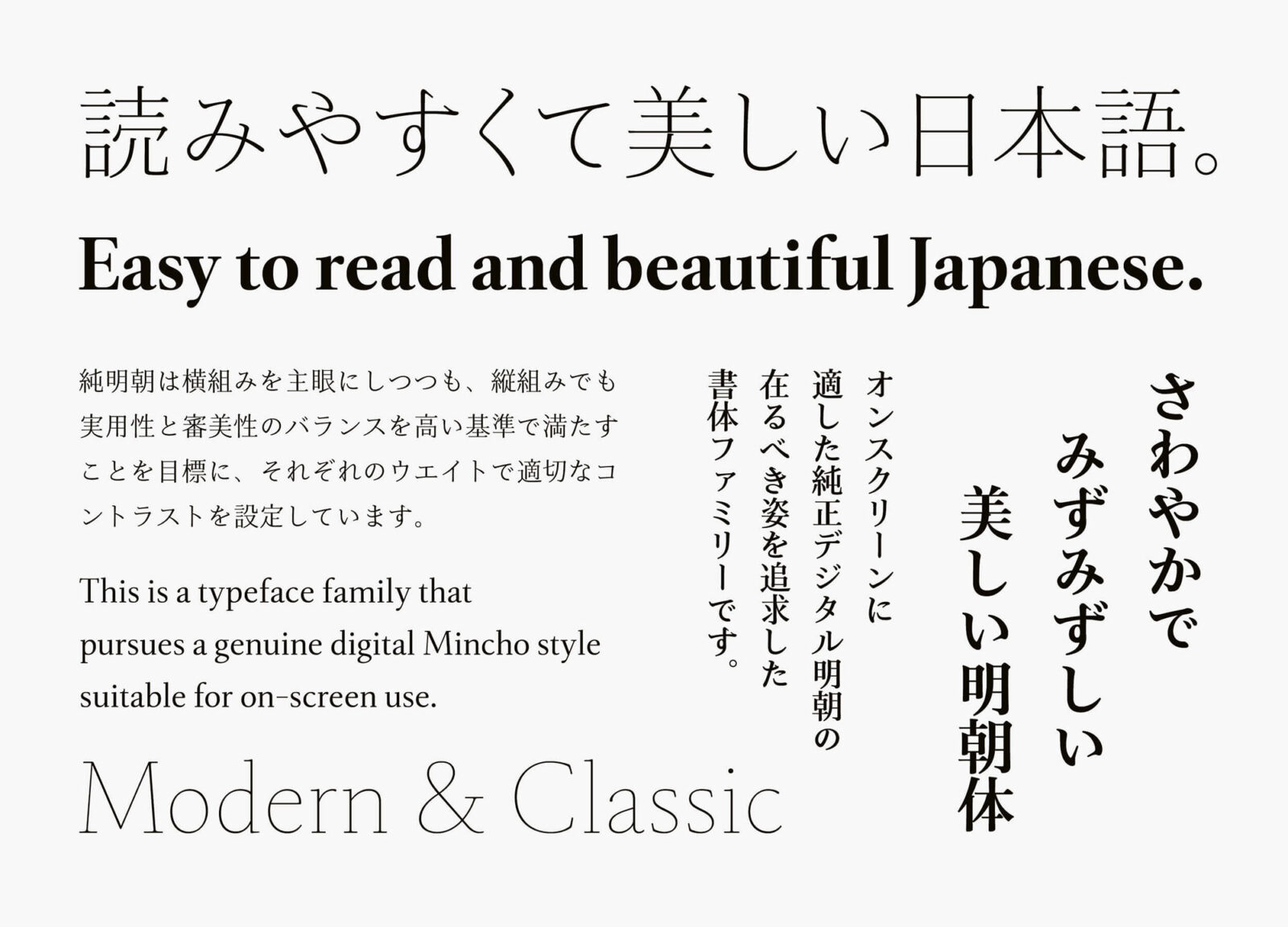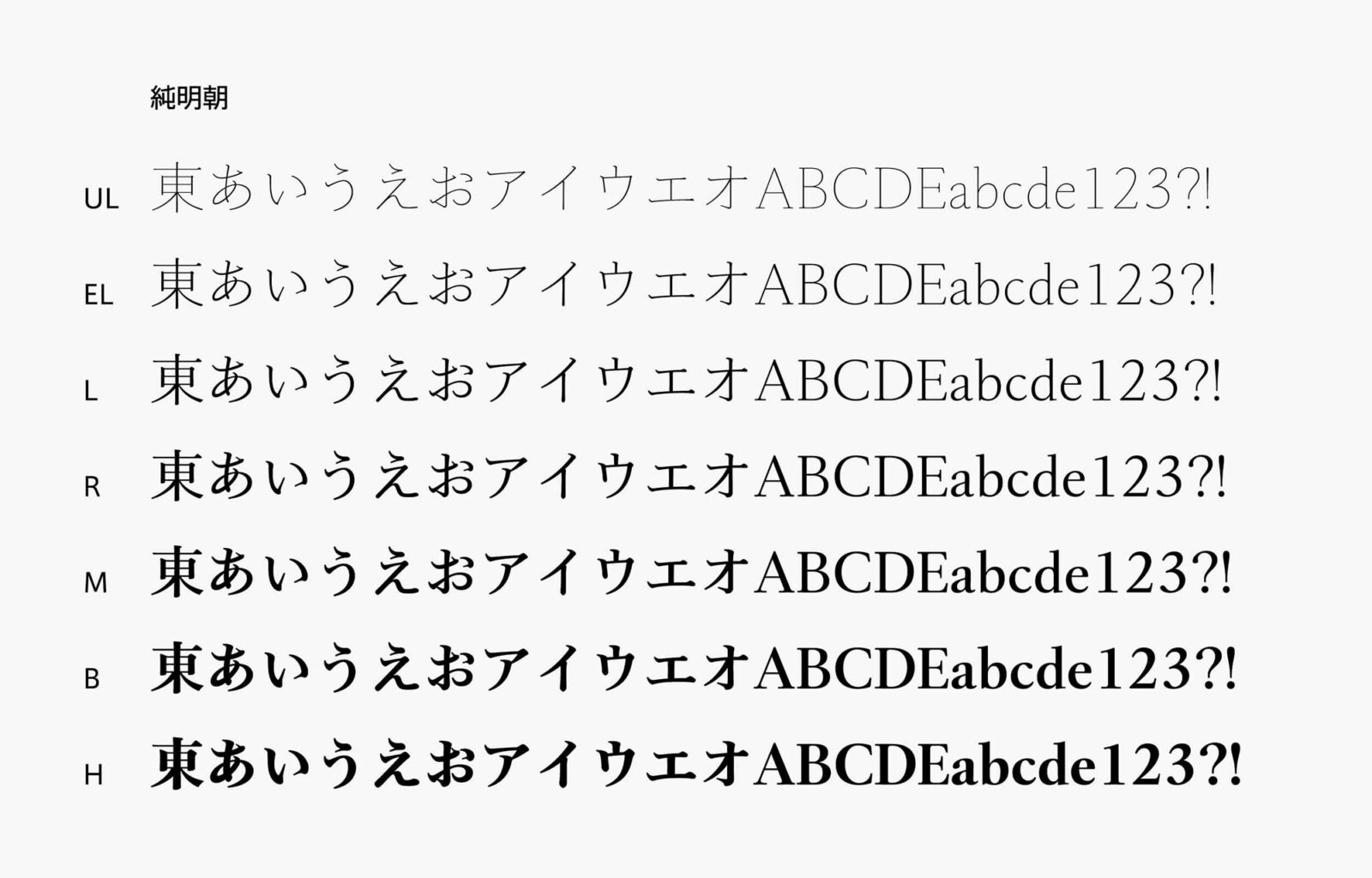
「横組みの日本語をもっと読みやすく、もっと美しく」をテーマにした書体
純明朝は「横組みの日本語をもっと読みやすく、もっと美しく」をテーマにした書体ファミリーで、安定した読み心地が得られるよう、それぞれのウエイトにおいて適切なコントラスト(縦画と横画の太さの比率)を設定しました。オンスクリーンで敬遠されがちな明朝体の弱点を克服するとともに、画面にうるおいを与えるべく明朝体の美しさを十分に引き出す書体設計をおこなっています。
純明朝は、横組みを主眼にしつつも、縦組みでも実用性と審美性のバランスを高い基準で満たすことを目標にしました。極端に強い個性を打ち出すのではなく、安定感を重視し、各ウエイトのコントラスト値を微妙に変えることですべてのウエイトで純明朝の印象が同じになるように調整をおこなっています。
タイププロジェクトの代表取締役 鈴木 功は、「純明朝は2015年に試作を開始し、書体が完成するまでに8年を要しました。とくに漢字の制作は、筆画の細部から骨格の設計に至るまで試行錯誤の連続でした。仮名のデザインも、オーソドックスでありながら新鮮な表情をもたせるのは容易ではありません。しかし我々は、読みやすくて美しいという目標に焦点をしぼり続けました。結果として、オンスクリーンに適した純正デジタル明朝体を完成させたと自負しています」と述べています。
純明朝ファミリーは、UL(ウルトラライト)、EL(エクストラライト)、L(ライト)、R(レギュラー)、M(ミディアム)、B(ボールド)、H(ヘヴィ)の7ウエイトで構成しています。ULとELは、キャッチフレーズやヘッドラインなどの用途で極細ウエイトならではの繊細な美しさを発揮します。Lは本文に最適なコントラストを設定したウエイトで、純明朝の中核をなすフォントです。Rは紙面・画面を問わずキャプションなどの小さなサイズで安心して使用できます。BとHは見出し用途で新鮮な印象を与えたいとき重宝するフォントです。